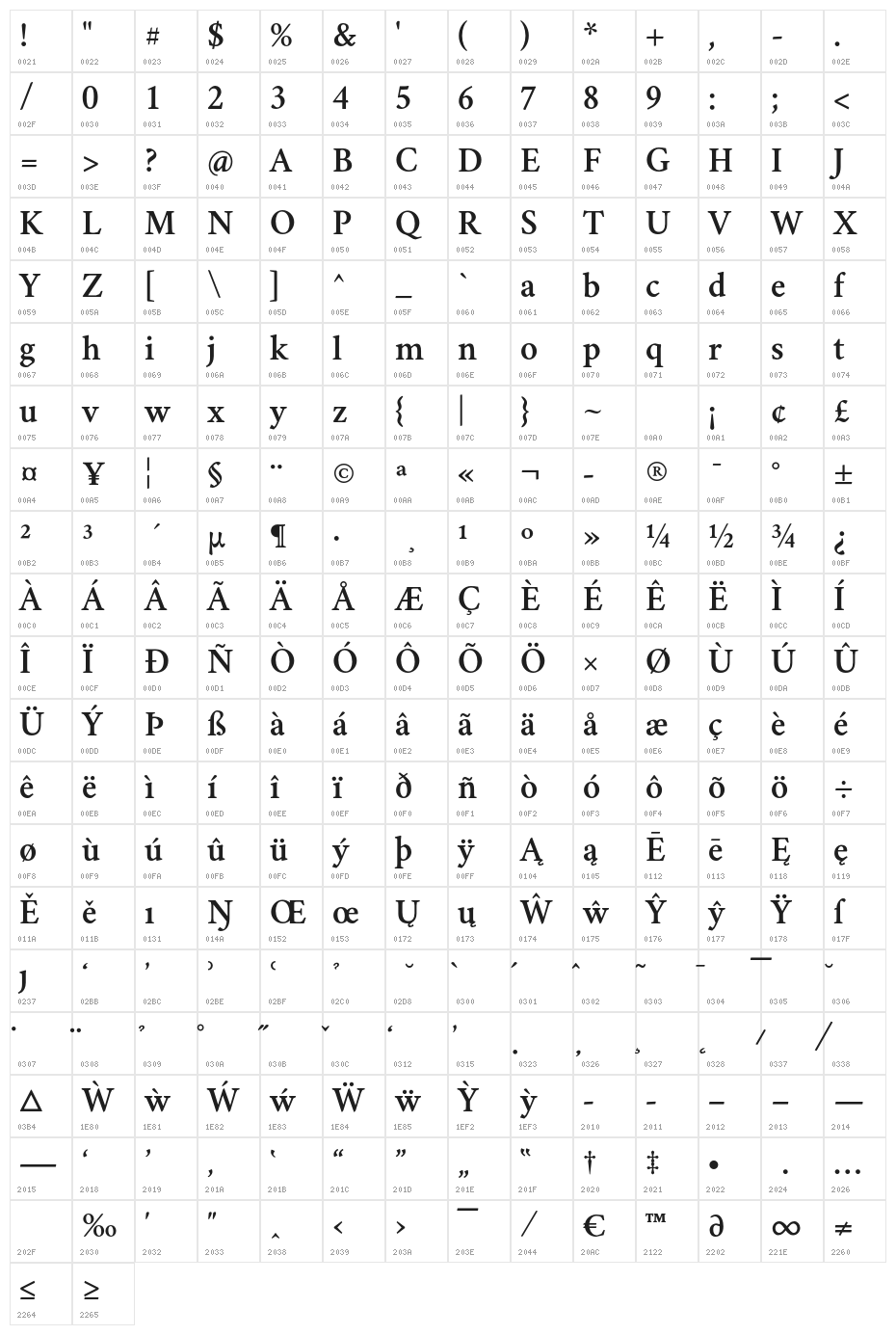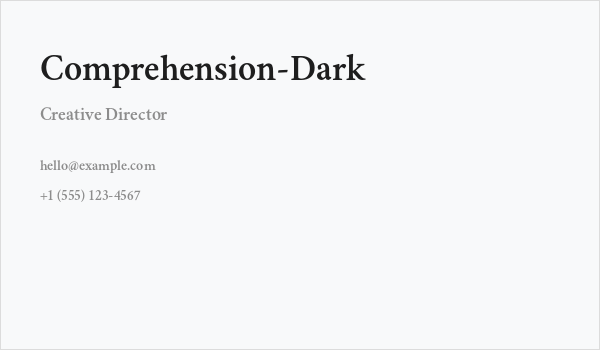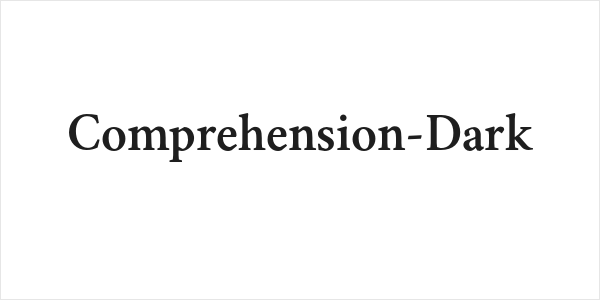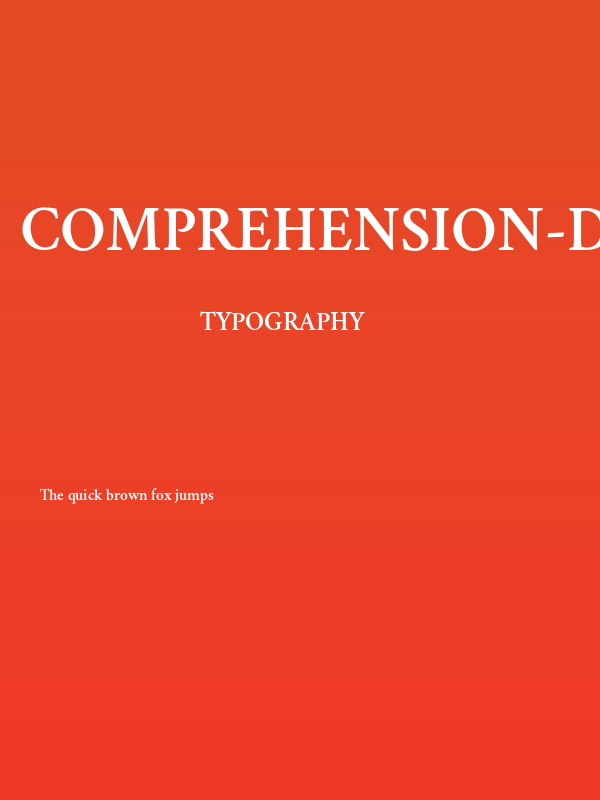
Comprehension-Dark Font
| Proiecte propuse | Ideal for editorial design, book covers, formal invitations, and branding projects that require a touch of elegance and tradition. |